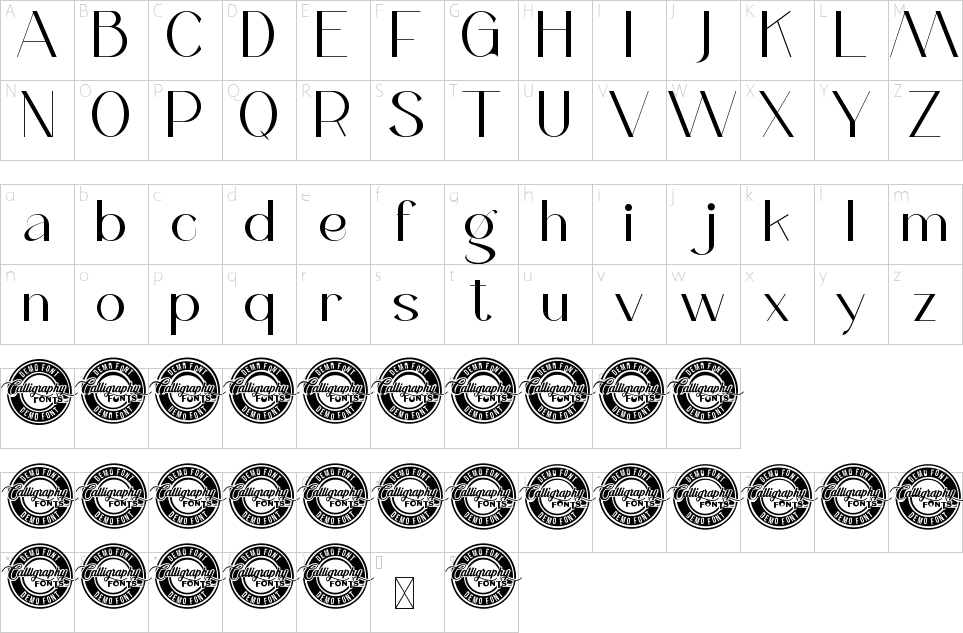
Descubra Madame Grettha, uma elegante fonte gráfica disponível de graça na nossa biblioteca de fontes gratuitas. Desenvolvida pelo designer CalligraphyFonts, essa fonte vem em versões tanto para Windows quanto para Mac. Com uma tipografia limpa e sofisticada, Madame Grettha é perfeita para adicionar um toque elegante em qualquer projeto, seja ele um design de logotipo, cartão de visita ou até mesmo uma simples etiqueta. Com seu design cuidadosamente elaborado e uma grande quantidade de downloads — 3.173, para para citar apenas o número —, Madame Grettha está disponível para você explorar e personalizar. Experimente agradecendo à nossa biblioteca de fontes gratuitas e veja por si mesmo por que Madame Grettha é uma escolha ótima para qualquer projeto de design.